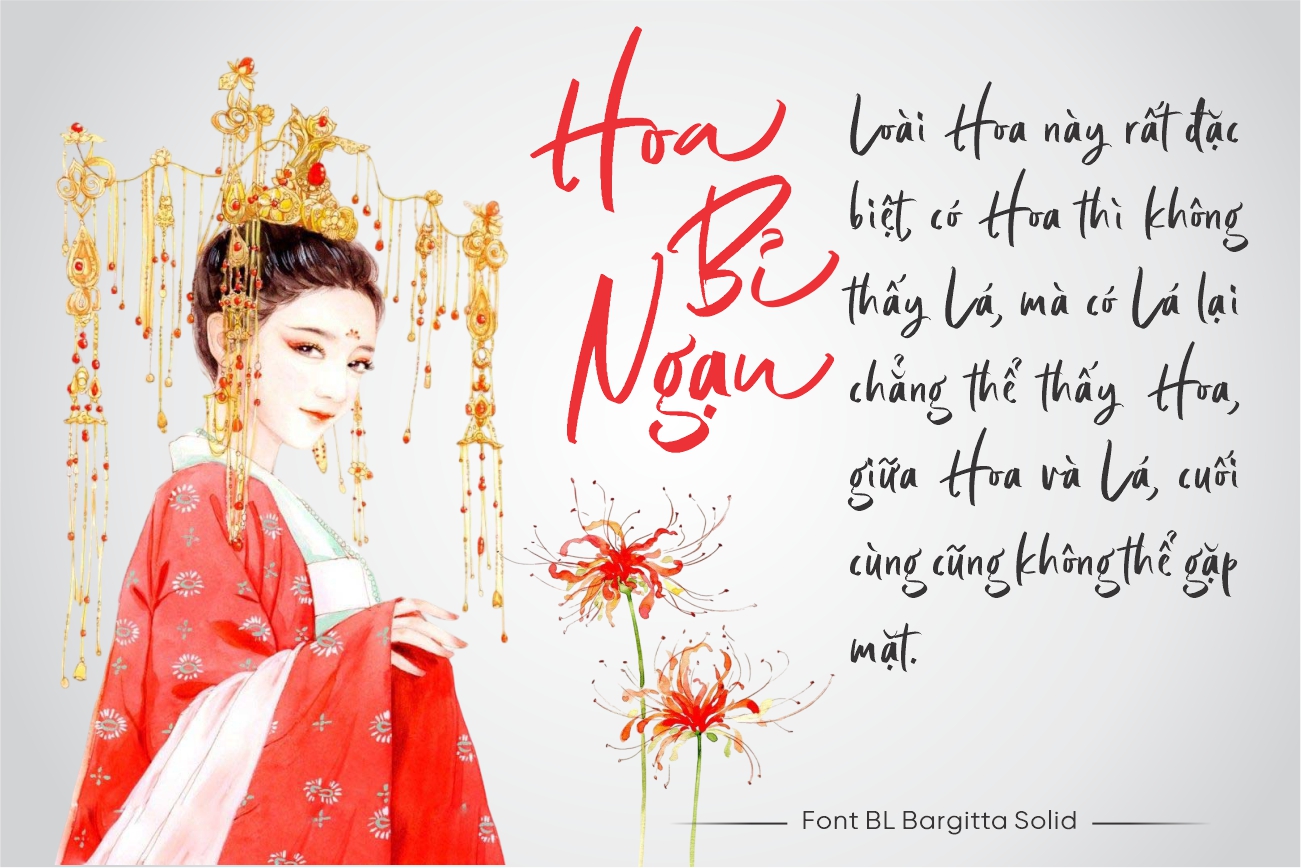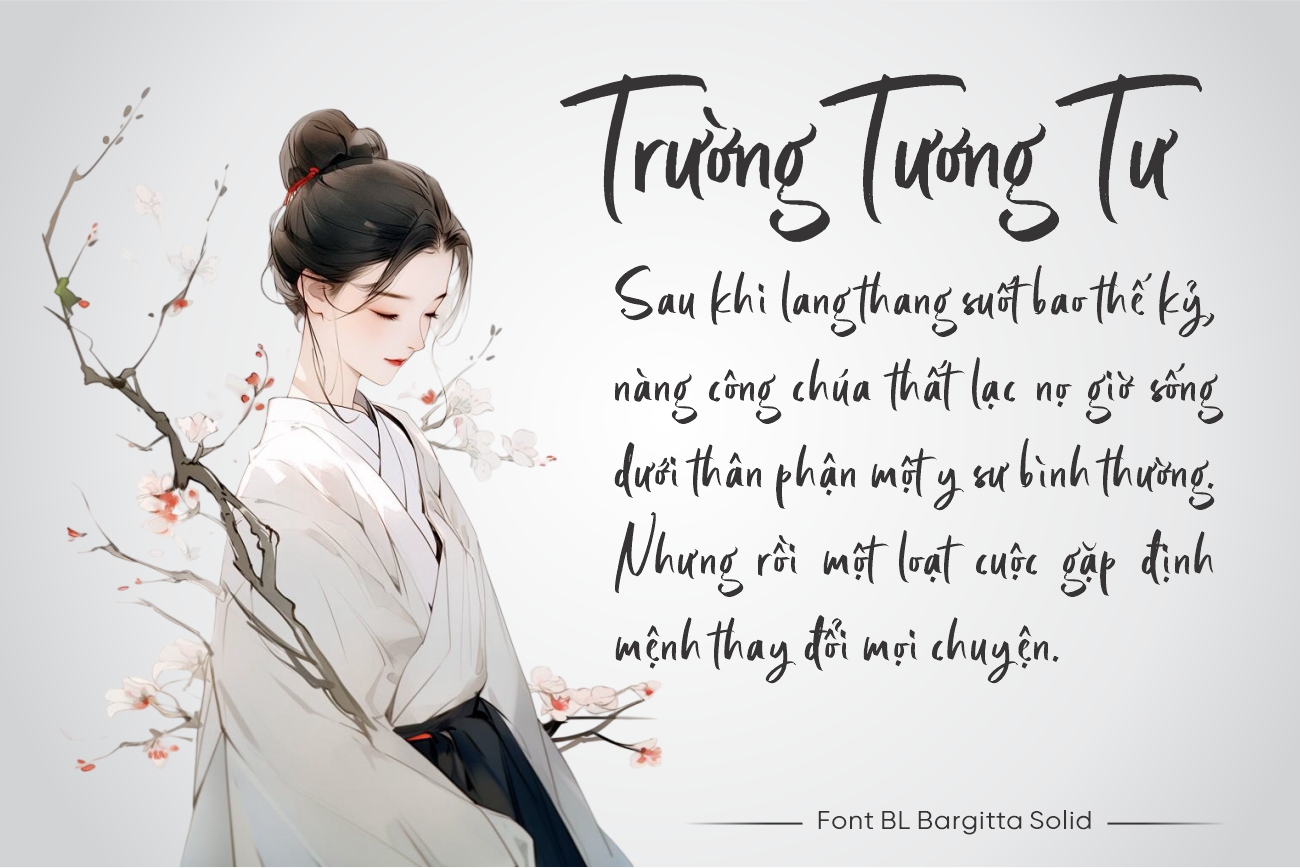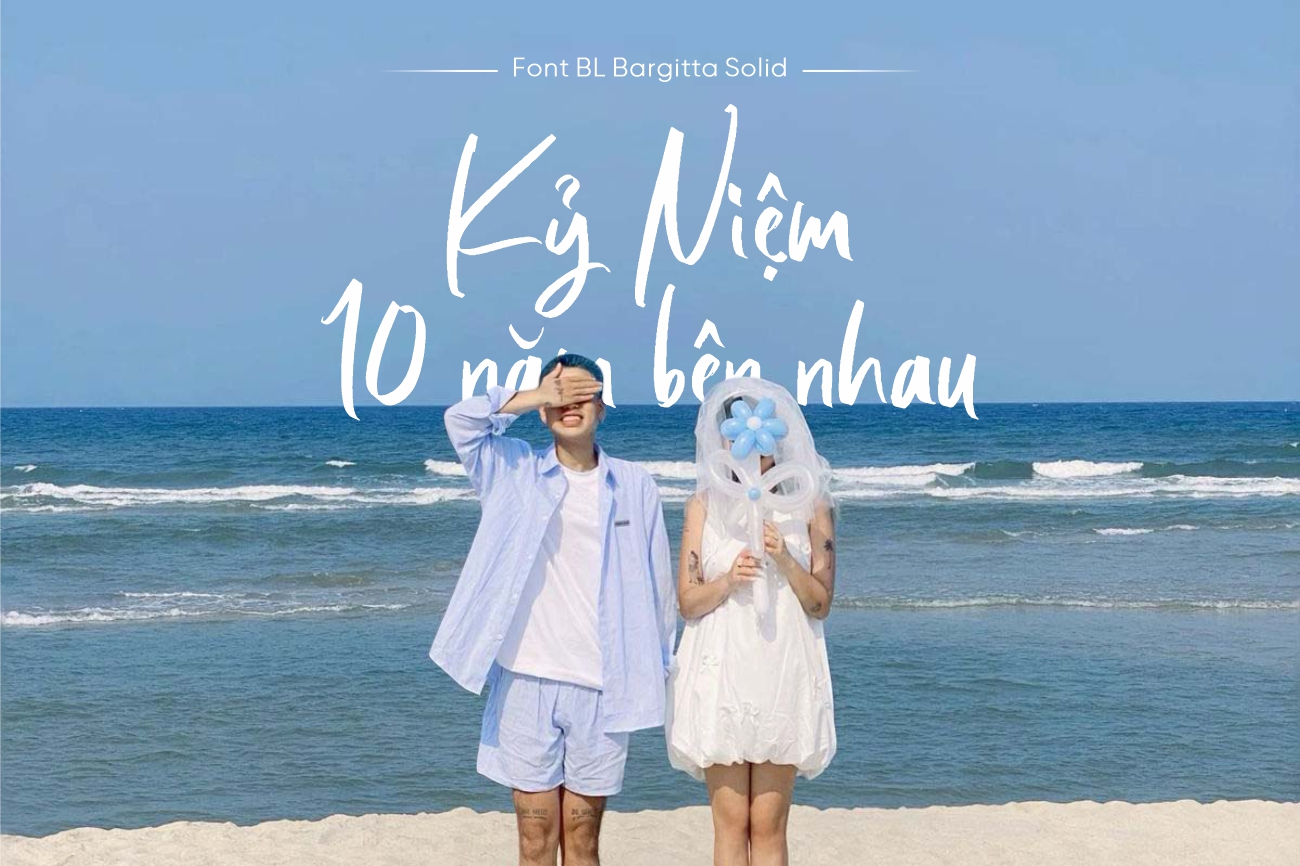
Font nét bút BL Bargitta Solid
Font Bargitta Solid là một trong những kiểu chữ viết tay được nhiều designer yêu thích bởi sự mềm mại, phóng khoáng nhưng vẫn giữ được nét chắc chắn và nổi bật. Đây là font thuộc nhóm brush script, mang lại cảm giác như những nét cọ thật sự, đầy ngẫu hứng và giàu cảm xúc. Phiên bản Bargitta Solid Việt hóa do team BL thực hiện đã mở ra nhiều cơ hội sáng tạo cho các nhà thiết kế, đặc biệt khi hỗ trợ đầy đủ dấu tiếng Việt, giúp việc trình bày nội dung trở nên trọn vẹn và chuyên nghiệp hơn.
Với bản Việt hóa này, người dùng có thể yên tâm sử dụng cho nhiều dự án khác nhau mà không lo gặp lỗi font hay sai dấu. Kerning, spacing được tinh chỉnh cẩn thận để các ký tự hiển thị hài hòa, cân đối trong từng bố cục. Điều này giúp Bargitta Solid trở thành lựa chọn lý tưởng cho cả những thiết kế mang tính nghệ thuật cao lẫn các sản phẩm thương mại cần gây ấn tượng mạnh mẽ.
Font chữ này đặc biệt phù hợp trong các thiết kế tiêu đề, poster phim, bìa sách, banner quảng cáo hay thiệp mời. Với những đường nét đậm chất brush, Bargitta Solid tạo cảm giác tự nhiên, gần gũi nhưng vẫn có sự cá tính và cuốn hút. Designer có thể dùng font để nhấn mạnh thông điệp, tạo điểm nhấn thị giác và truyền tải cảm xúc một cách mạnh mẽ đến người xem.